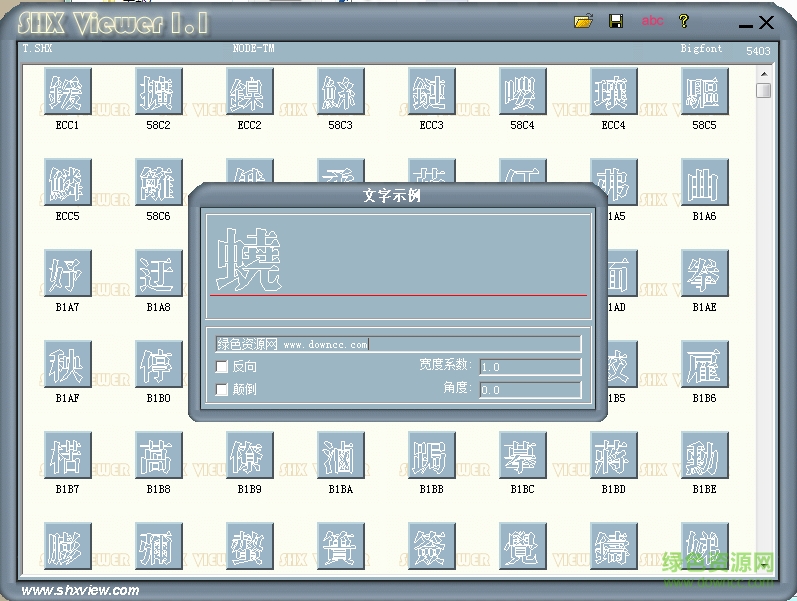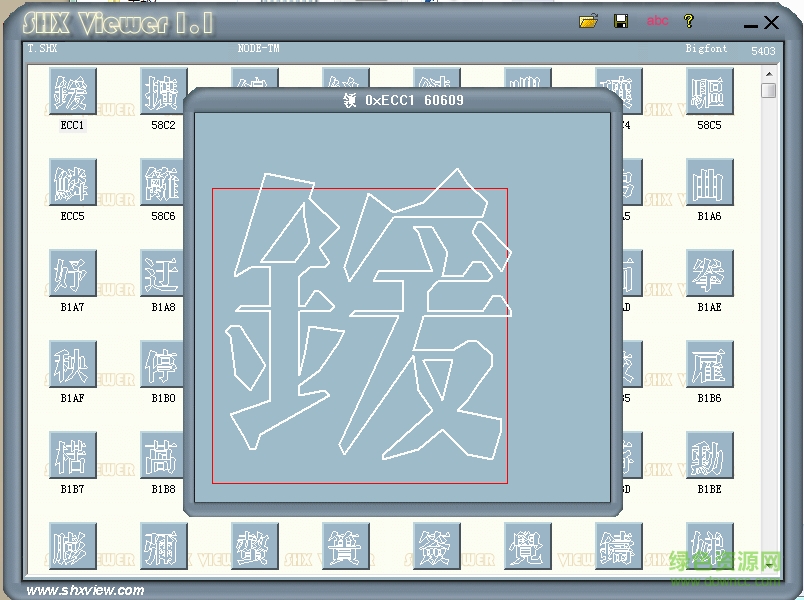
t.shx是一款以宋體為模板的cad字體,屬于大字體系列,鏤空的造型讓你平面設(shè)計(jì)、文字編輯更顯獨(dú)特韻味,喜歡的朋友來綠色資源網(wǎng)即可免費(fèi)使用哦!
t.shx擁有5403個(gè)漢字,屬于bigfont,包含繁簡字體,字體不是很多部分字體可能無法顯現(xiàn),單字體結(jié)構(gòu)勻稱,白邊空心顯得更加立體有層次感。
autocad也有自己的字庫,在fonts目錄里。字體文件以shx為擴(kuò)展名,稱為shx字體。最初的shx字體支持的是ANSI字符,后來擴(kuò)大到支持非ANSI字符,也就是大字體或bigfont,用雙字節(jié)儲(chǔ)存,這也就是為什么叫大字體的原因。但也僅作為文字處理上的補(bǔ)丁,要單獨(dú)指定。